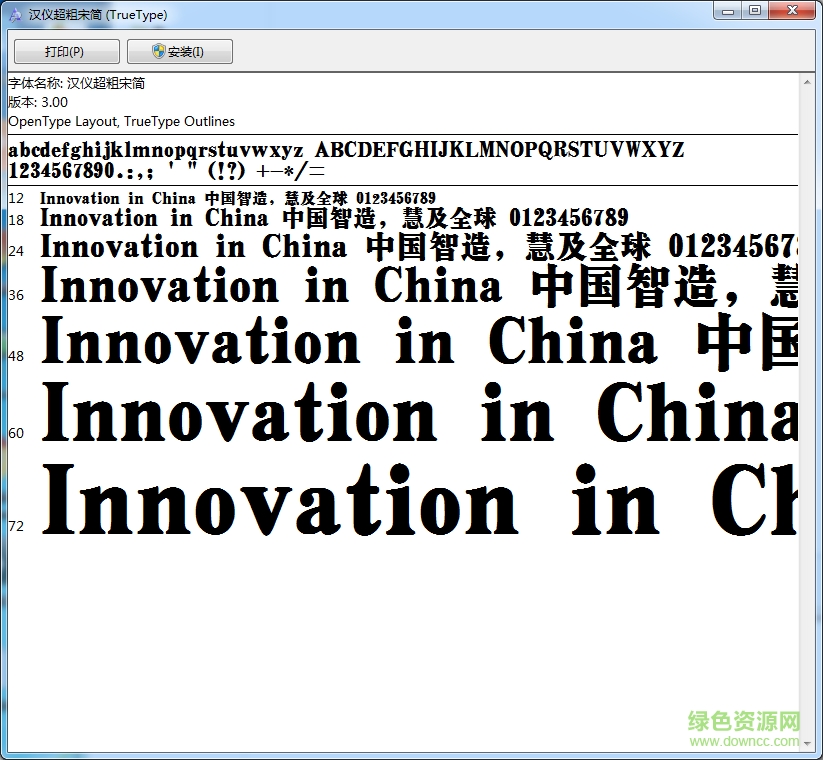
hyaogj是什么字體?hyaogj是一款超粗的漢儀宋體字體,該字體挺秀均勻,風(fēng)格典雅,實(shí)用性強(qiáng),可用在各類文章、雜志的排版設(shè)計(jì)方面,歡迎大家免費(fèi)下載!
該字體可延展出標(biāo)宋、書宋、大宋、中宋、標(biāo)宋、仿宋、細(xì)仿宋等,種類繁多,差別不大,都常用于正文。
在國內(nèi)的印刷行業(yè),字種主要有漢字、外文字、民族字等幾種。漢字包括如宋體、楷體、黑體等等。外文字又可以依字的粗細(xì)分為白體和黑體,或依外形分為正體、斜體、花體等等。民族字是指一些少數(shù)民族所使用的文字,如蒙古文、藏文、維吾爾文、朝鮮文等。